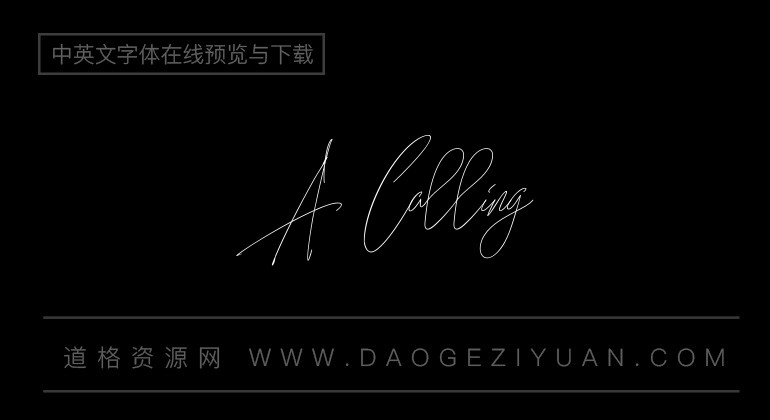
A Calling是一款简洁的手写字体,它被设计为一种有着自然的手写风格的字体。它的字形简单,但却很有表现力,可以用于创建时尚的标题和标签。它的字体细节清晰可见,可以在大型屏幕上使用,而且可以很好地支持多种语言。内容介绍
A Calling是一款非常不错的手写艺术字体,具有很好的视觉感,适合于文化类的宣传设计、商业类品牌的广告和产品包装设计以及个性化文字排版等较多场景。